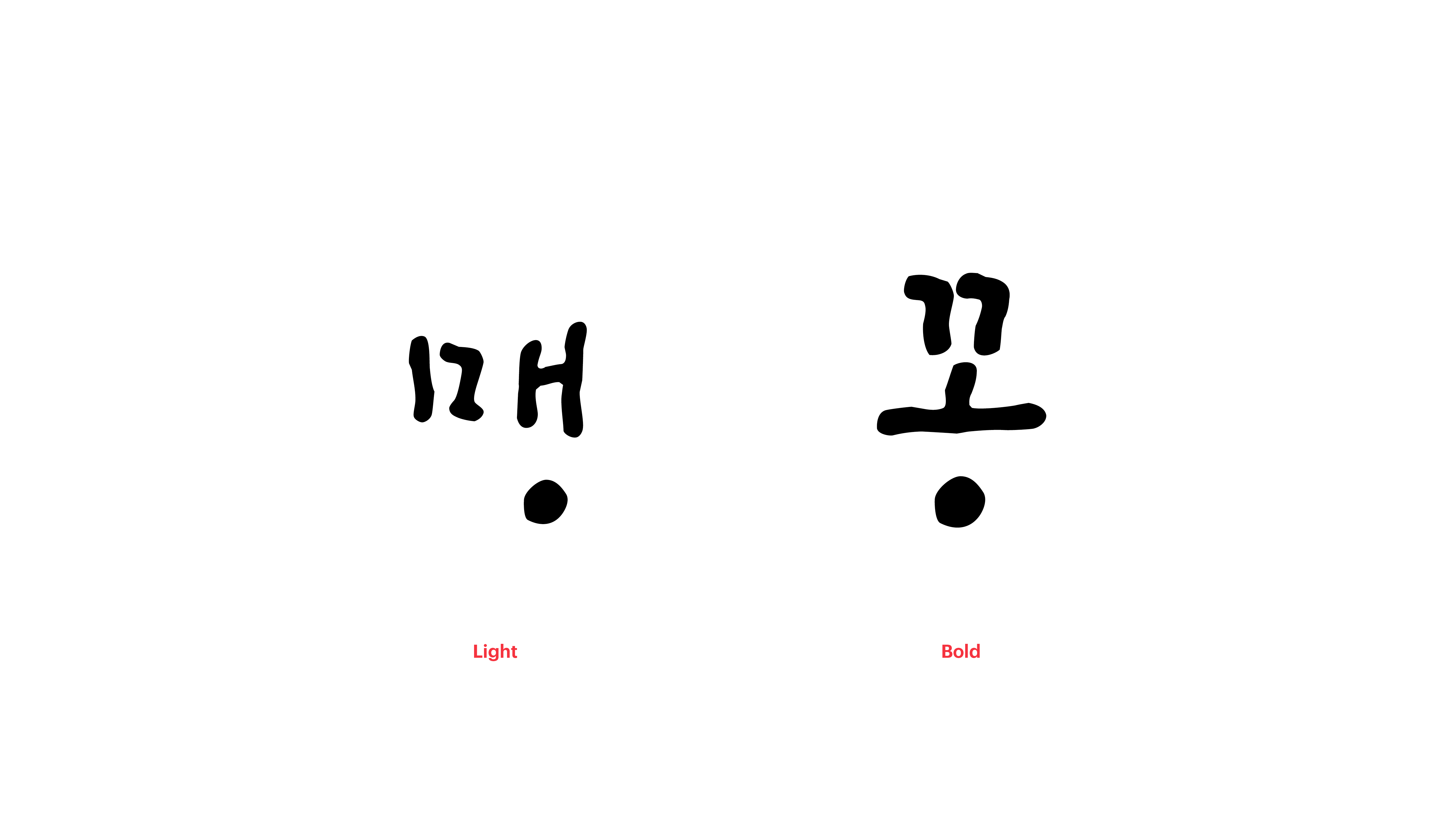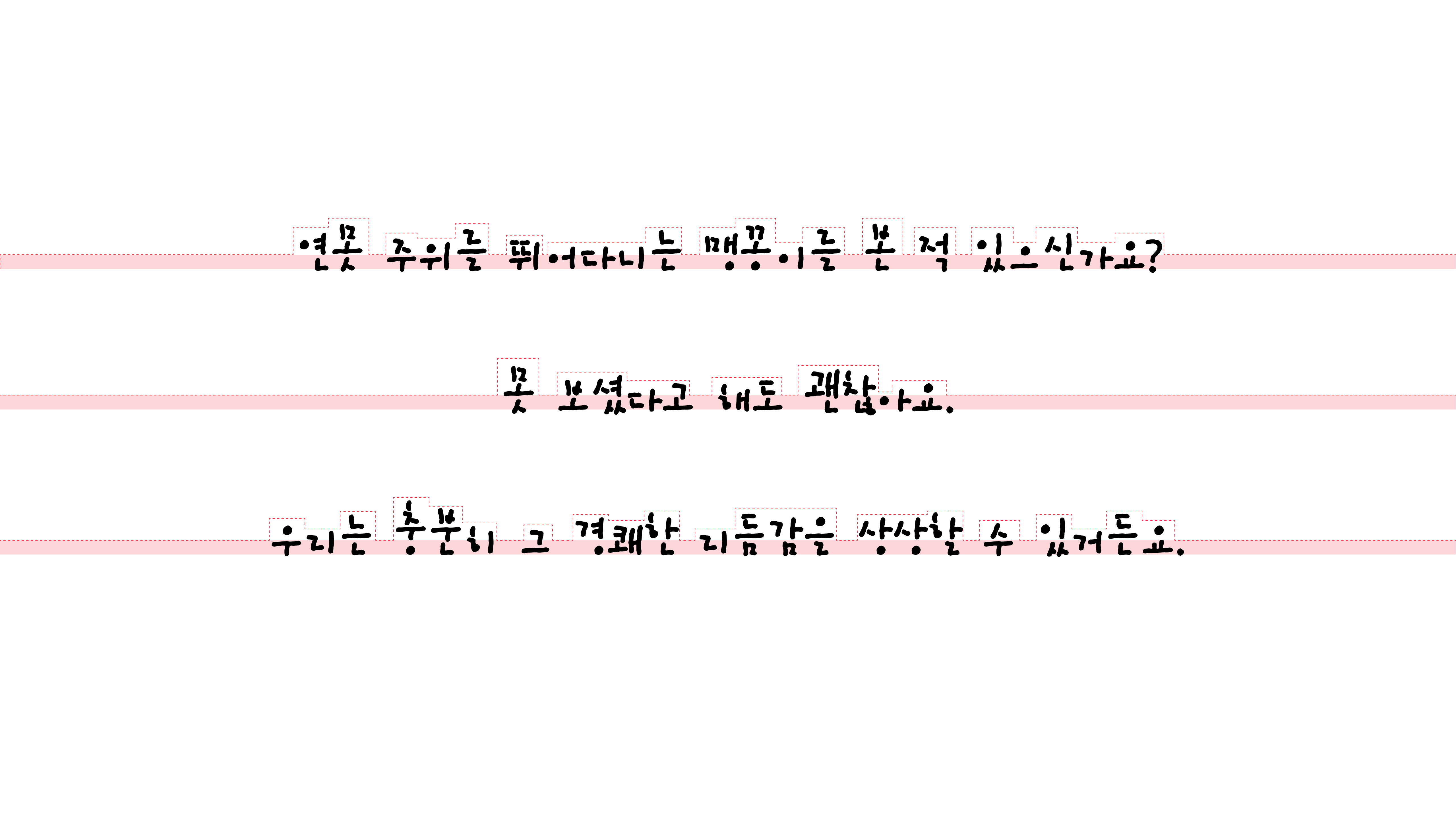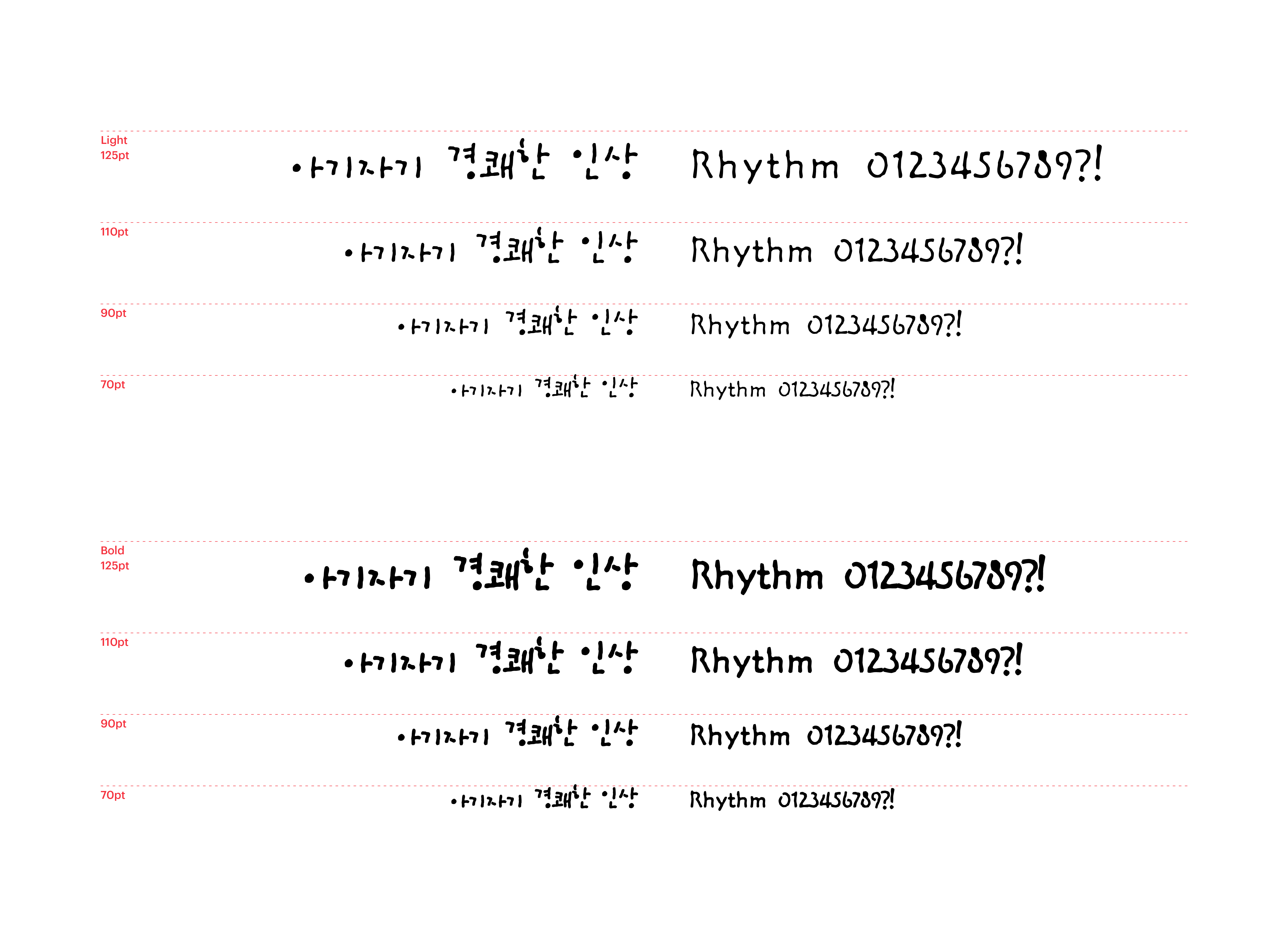
맹꽁이
Yoon 맹꽁이
연못 주위를 뛰어다니는 맹꽁이를 본 적 있으신가요? 못 보셨다고 해도 괜찮아요. 맹꽁이체를 보면 우리는 충분히 그 경쾌한 리듬감을 상상할 수 있거든요. 폰트 하단에 글줄을 맞추어 아기자기하면서도 정돈된 인상을 주는 맹꽁이체. 어쩐지 방금 막 피어오르기 시작한 아이디어를 기록하는 데 사용하고 싶어집니다.